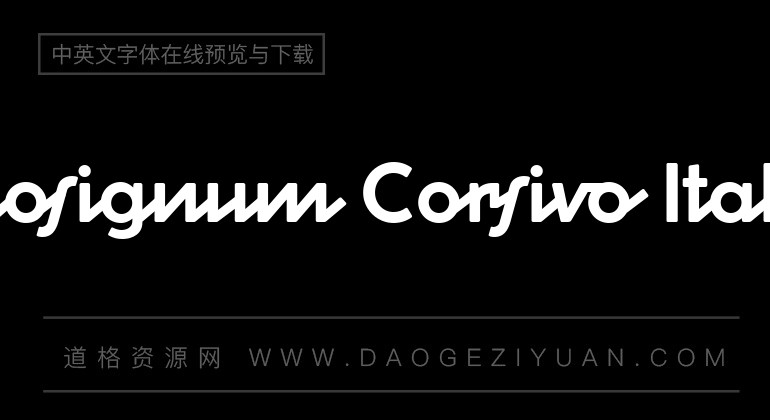
Cocosignum Corsivo Italico
Cocosignum Corsivo Italico 是一款精美的意大利式手写体字体,它拥有温柔、优雅的外观,可以帮助您创造出精致的文字效果。字体特点有:细腻的笔画,温暖的色调,圆润的字形,令人印象深刻的细节,以及几何形状的结合。Cocosignum Corsivo Italico 字体适用于文字、标题、图形设计等多种场景,可以为您的设计提供独特的感觉,添加更多的灵动性和细节感。
Cocosignum Corsivo Italico是一款非常不错的手写艺术字体,具有很好的视觉感,适合于文化类的宣传设计、商业类品牌的广告和产品包装设计以及个性化文字排版等较多场景。